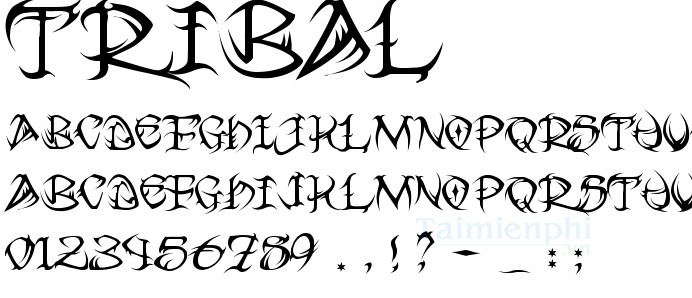
Fonts Tattoo
Fonts Tattoo là bộ font chữ được thiết kế khá đẹp mắt sử dụng trên máy tính cá nhân cho các ứng dụng, Font xăm hình với các đường nét font chữ khá đẹp mắt đã được việt hóa bộ font chữ này đang được các kỹ sư đồ họa sử dụng khá nhiều trong công việc thiết kế của mình.
Những đặc điểm chính của Fonts Tattoo:
- Font chữ đẹp, độc đáo cho máy tính